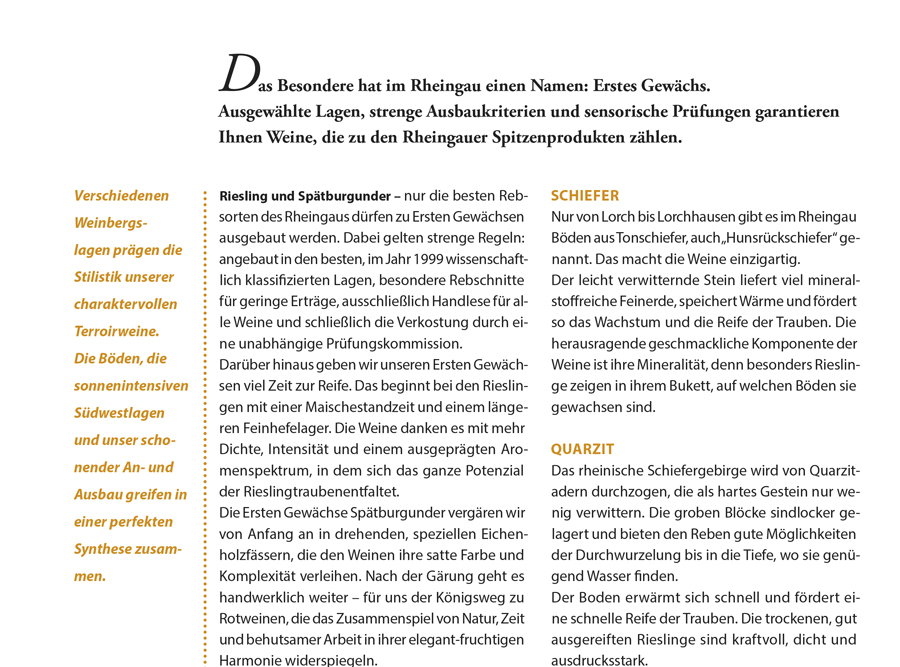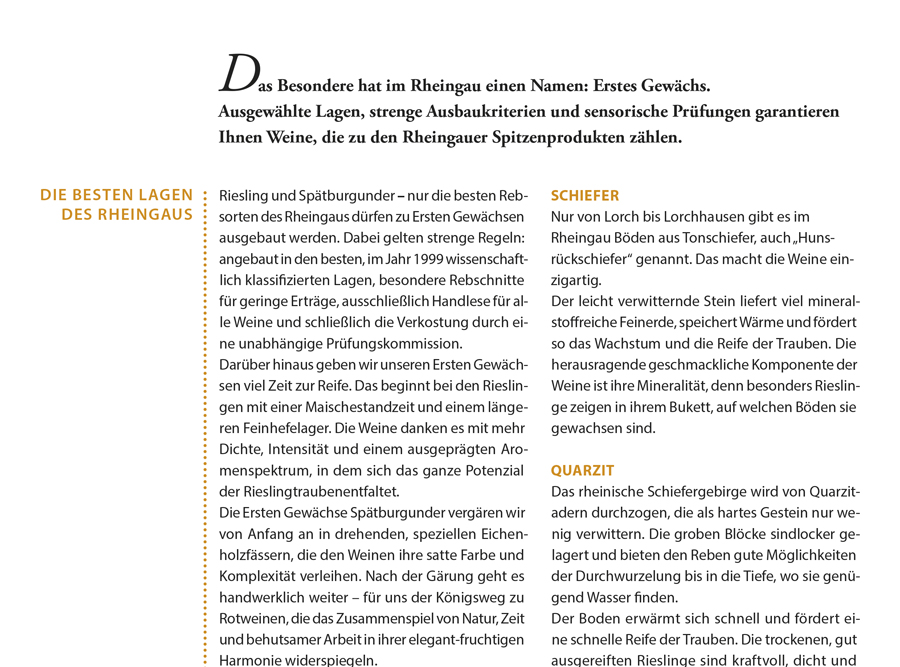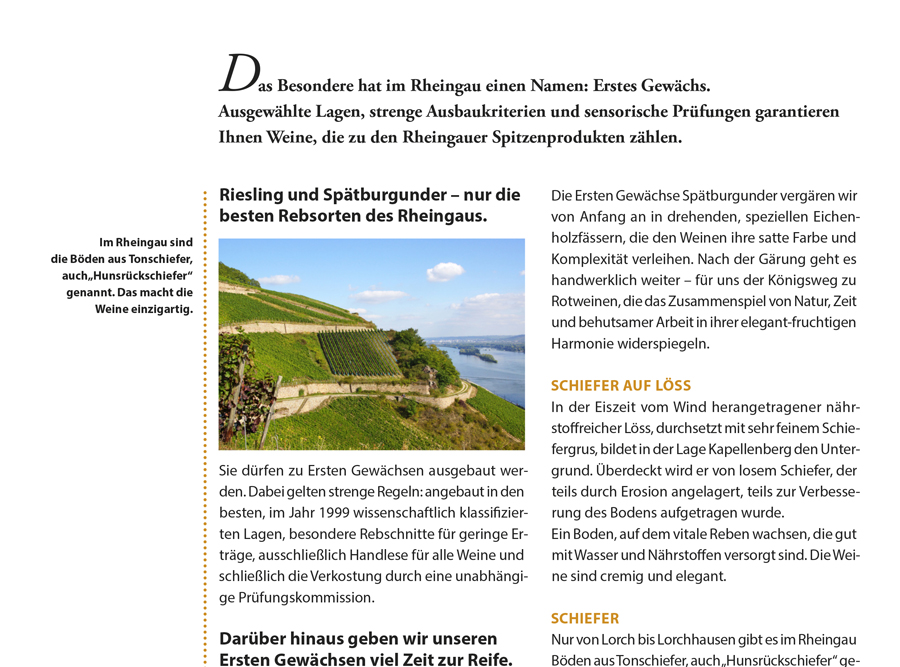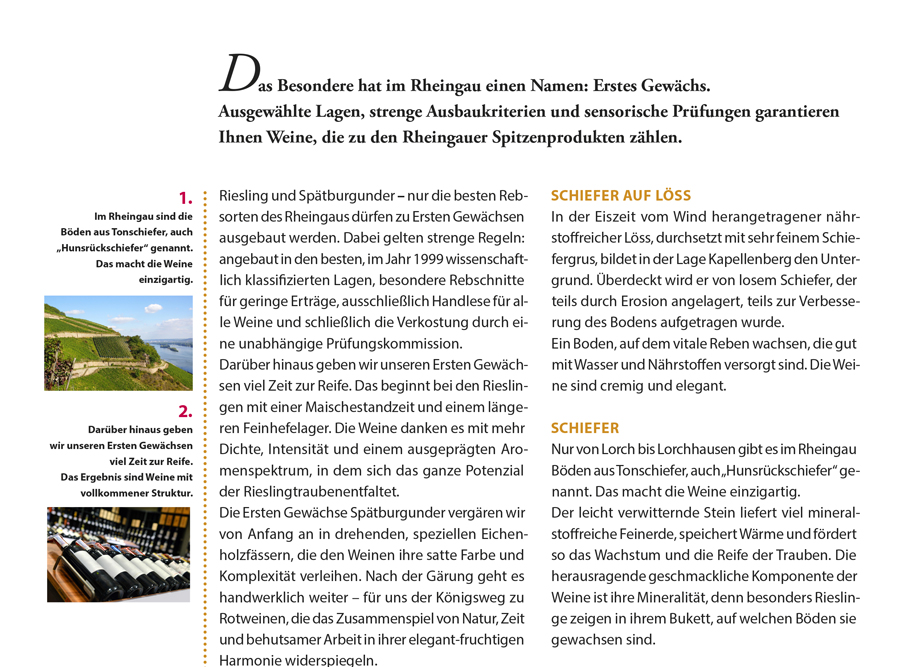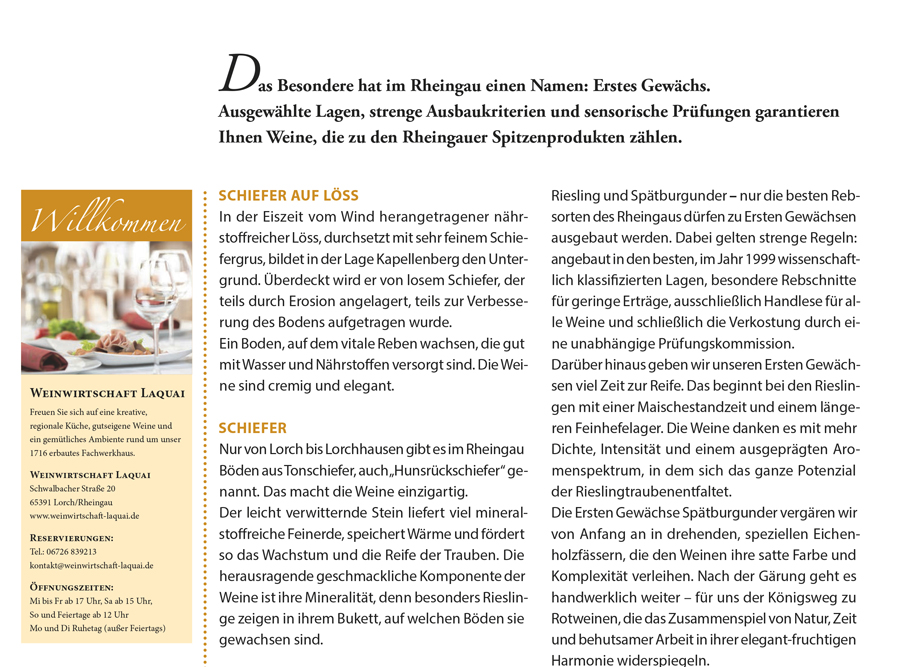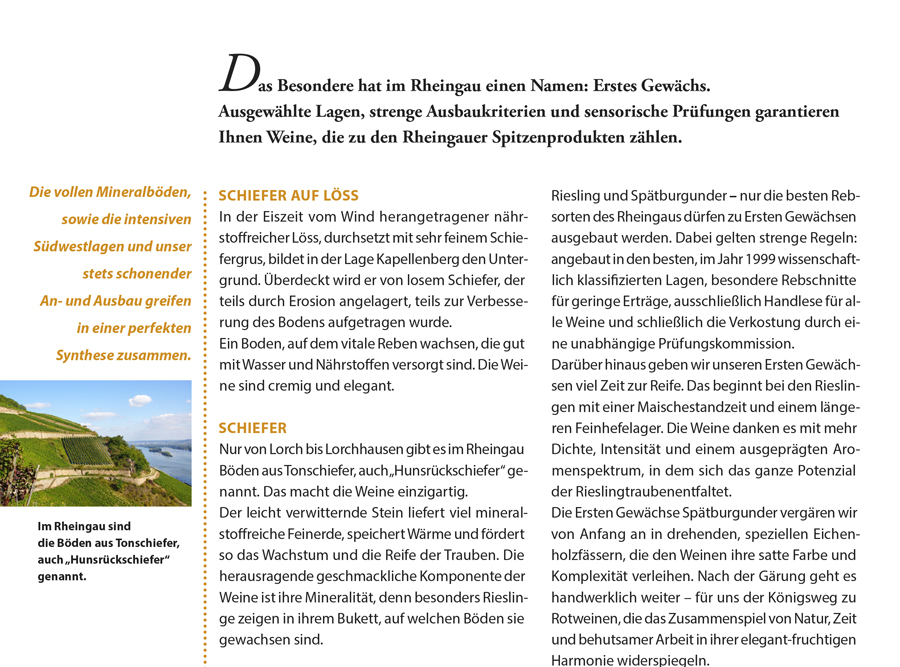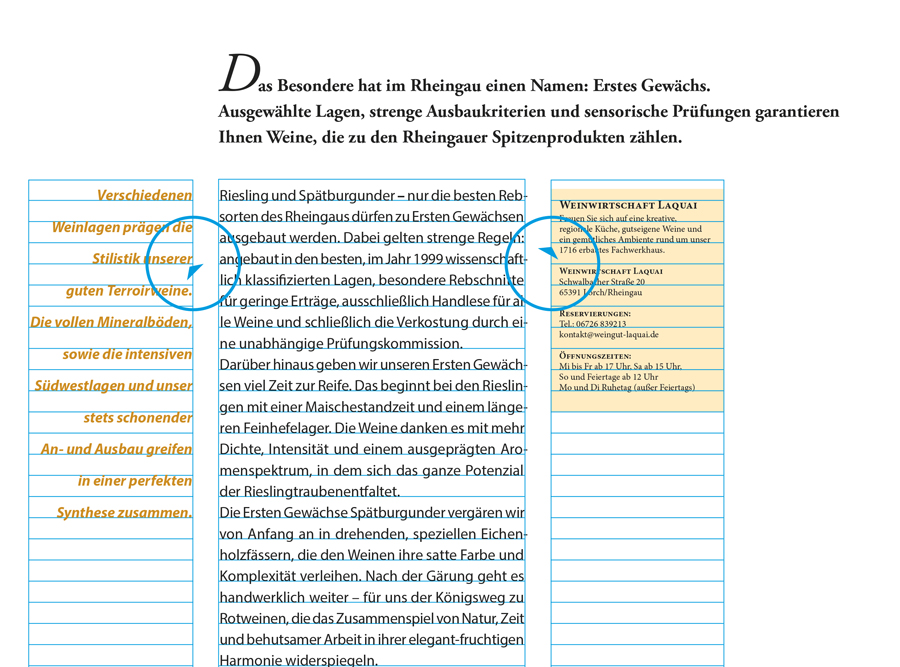
Am Rande bemerkt: Marginalien in der Typografie und wie man sie im Layout richtig anwendet
Einsatz von Marginalien in einem alten Schritstück
Marginalsatz ist eine der schönsten gestalterischen Formen in der Typografie und dabei vielseitig und kreativ im Layout einsetzbar. Was Marginalien sind, wo ihre Ursprünge liegen, welche Wirkung sie in einem Layout haben und vor allem wie man sie in InDesign richtig anwendet – damit beschäftige ich mich in diesem Blogeintrag.
Was ist Marginalsatz?
Marginalsatz oder Marginalien haben – wie vieles in der Typografie – eine lange Tradition. Natürlich kommt der Begriff aus dem Lateinischen und bedeutet: margo = Rand; marginalis = zum Rand gehörig. Vereinfacht gesagt sind Marginalien Bemerkungen oder Informationen zum Text, die an den Rand gesetzt sind. Dabei ist es nicht immer ganz eindeutig, ob es sich bei Marginalien um Bildtexte, Texteinleitungen, Zwischenüberschriften oder Texte der 2. Informationsebene, wie beispielsweise Fußnoten, handelt. Dabei können Marginaltexte auch Randinfos sein, die nicht direkt etwas mit dem Grundtext zu tun haben. Auch habe ich schon Kombinationen von Text und Bild als Marginalien angewendet. Das kann sehr gut aussehen und sinnvoll sein in der Organisation von Informationen auf einer Seite.
Tradition aus Klosterschreibstuben
Marginalien sind bereits seit dem 10. Jahrhundert bekannt. Oft wurden geistliche und religiöse Schriften von den Klöstern zur Abschrift in Auftrag gegeben. Dabei sah man bei der Anfertigung der Schriften (Inkunabel und auch Kodex) breite Randspalten an den Außenrändern vor. Sie dienten weniger dazu, das Schriftbild beim Blättern der Seiten zu schützen, sondern vielmehr für nachträgliche handschriftliche Einträge. Jeder Abt eines Klosters behielt sich nämlich vor, die heilige Schrift nach seiner Auffassung oder Auslegung anders zu interpretieren. Und das konnte man am einfachsten auf den breit angelegten äußeren Randspalten.
Organisation von Information
Im Corporate Design sehen Marginalien heute nicht nur schön aus. Für mich ergeben sie häufig Sinn bei der Organisation von Informationen. Richtig angewendet können sie die Botschaft einer Magazin- oder Buchseite deutlich verbessern.
Hier ein paar Beispiele, wie Marginalien eingesetzt werden können:
Marginalien in der InDesign-Anwendung
Im Folgenden möchte ich Ihnen noch ein paar Tipps dazu geben, wie Sie Marginalien in InDesign richtig einsetzen.
Layout
Marginalien sind eine typografische Form. Deshalb sollte man sie für meinen Geschmack anders behandeln als den Grundtext. In der Layoutanwendung gehören Marginalien nicht unbedingt in den Satzspiegel, sie sollten in der Regel an den äußeren Seitenrändern stehen. Achten Sie darauf, genügend großen Raum einzuplanen, wenn Sie den Satzspiegel oder das Gestaltungsraster für eine Doppelseite einrichten.
Schriftart
Mut zum Anderssein: Marginalien sollten nicht die gleiche Schriftgröße oder Schriftart haben wie die Grundschrift. Trauen Sie sich, Schriften zu mischen oder auszuzeichnen! Auch kann die Schriftgröße gegenüber der Grundschrift deutlich kleiner oder auch größer sein.
Satzart
Da die Spaltenbreite einer Marginalie deutlich kleiner sein sollte als die der Grundschrift, sollten Marginalien der besseren Lesbarkeit wegen eher als Flattersatz gesetzt werden – egal, ob die Grundschrift in Blocksatz oder Flattersatz ausgezeichnet ist.
Grundlinienraster
Marginalien müssen nicht zwingend in das Grundlinienraster eingebunden werden. Jedoch sollte die erste Zeile stets auf der Grundlinie stehen und mit der ersten Zeile des Grundtextes registerhaltig sein. Wenn die Marginalie in einer kleineren Schriftgröße als die Grundschrift gesetzt wird, können die Zeilenabstände auch alignieren, d. h. der kleinere Zeilenabstand wird alle paar Zeilen mit denen der Grundschrift in der Spalte registerhaltig sein. Hier ein Beispiel dazu:
Marginalien anwenden in Typografie und Layout
Zeilenabstände im Grundlinienraster, die alignieren: Der Zeilenabstand im Grundlinienraster beträgt 14 Punkt. Der Zeilenabstand der Marginalie beträgt 21 Punkt und ist nicht im Grundlinienraster eingebunden. Jede vierte Zeile der Marginalien aligniert dann mit der Grundlinie der Grundschrift (Markierung rechts).
Wie immer hat auch mein Typo-Assistent Zitzero noch ein paar Tipps zum Thema Marginalien:
Mein Typo-Assistent Zitzero
Wenn Sie mit Marginalien arbeiten:
• Marginalien strukturieren die Kommunikation einer Seite und können angewendet werden als Textvorspann, Zwischenüberschrift, Bildunterschrift oder zusätzliche Randinfo.
• Marginalien gehören nicht unbedingt in den Satzspiegel; benötigen aber eine große Randspalte.
• Marginaltexte stehen in aller Regel an den Außenrändern einer Seite und sind kleiner als die normale Satzbreite der Grundschrift.
• Marginaltexte können sich typografisch in der Schriftmischung oder Schriftauszeichnung von der Grundschrift unterscheiden.
• Sie müssen nicht in das Grundlinienraster eingebunden werden; die erste Zeile sollte aber registerhaltig sein.